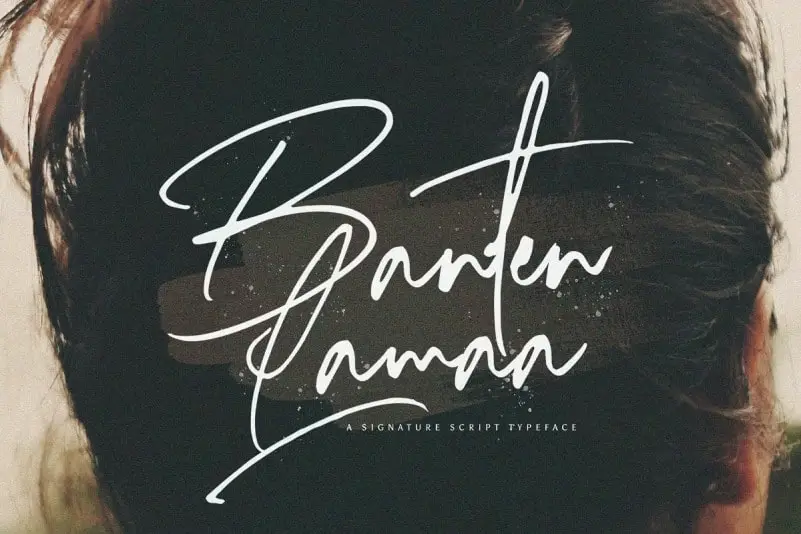
Banten Lama Handwritten Font – Fonte Grátis
Banten Lama Handwritten Font
A Banten Lama Handwritten Font é uma escolha perfeita para designers buscando uma combinação única de elegância moderna com a autenticidade do estilo de escrita à mão. Desenvolvida por StringLabs, essa fonte de escrever em letra cursiva apresenta linhas bem redondas e um toque refinado que criam uma harmonia perfeita entre funcionalidade e beleza. Ideal para aplicar em logos, materiais de mídia social ou qualquer projeto que busque destacar-se com um estilo único, a Banten Lama Handwritten é a fonte certa para criar designs memoráveis. Que tal explorar como essa letra curiosa pode transformar sua próxima criação visual?